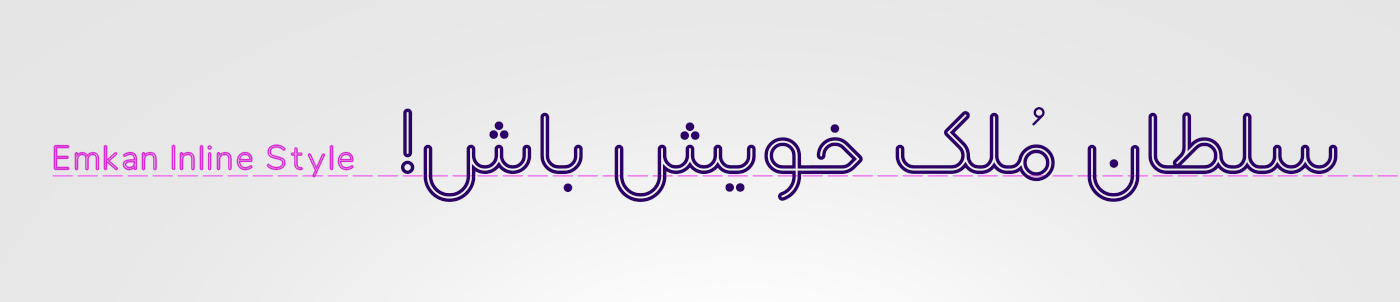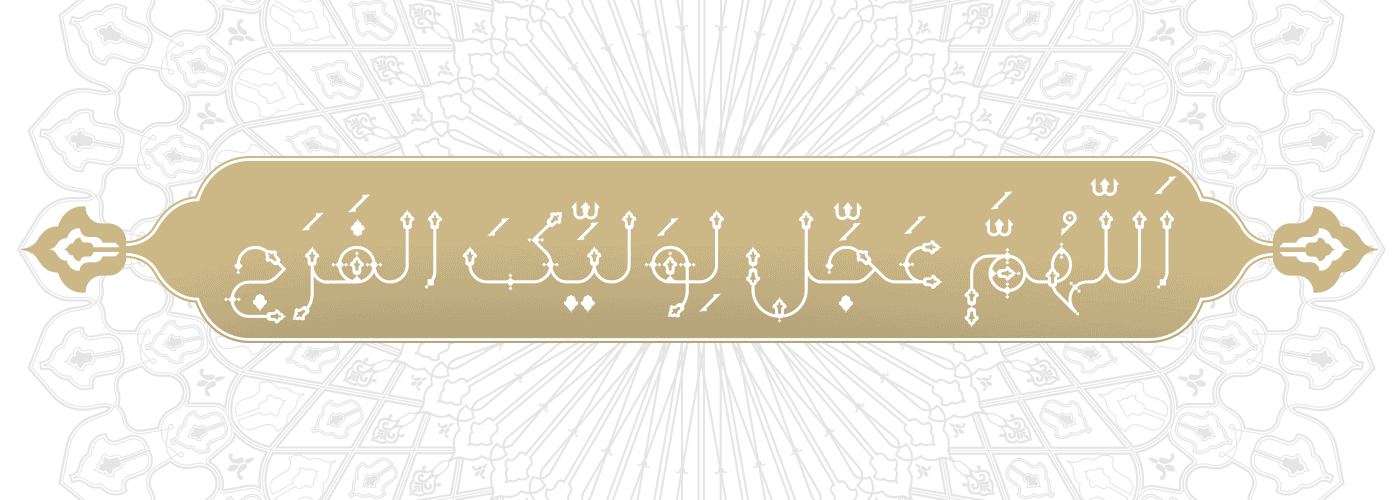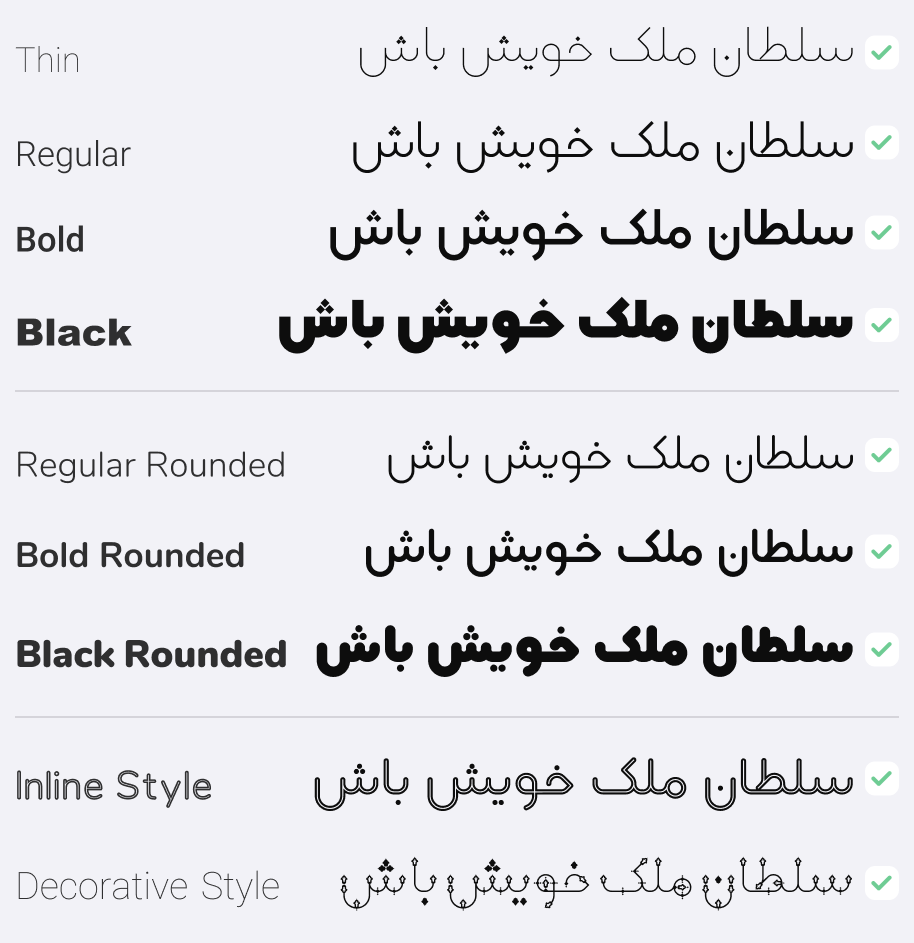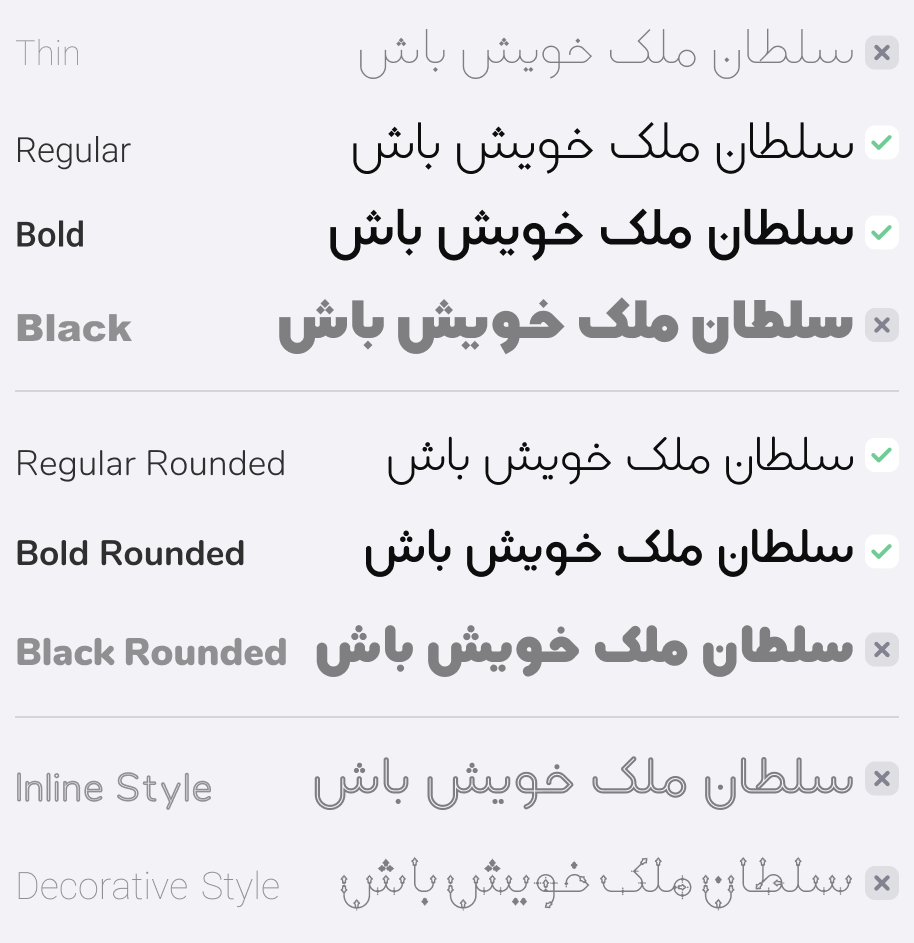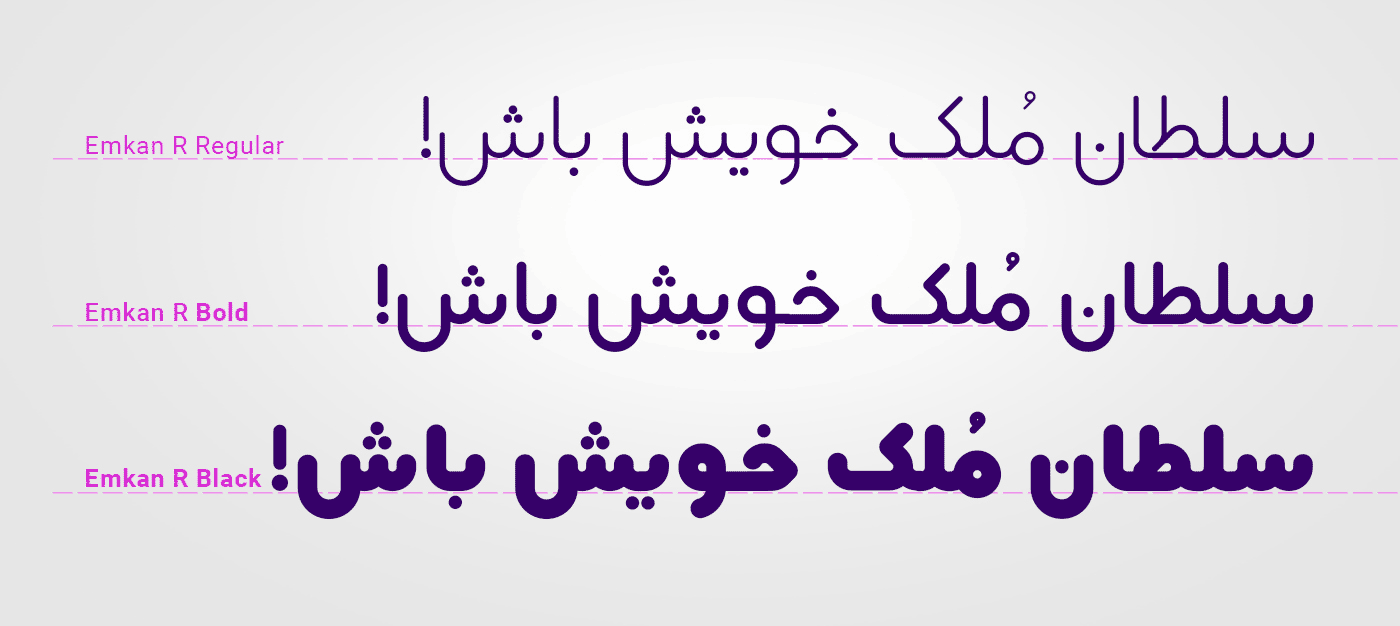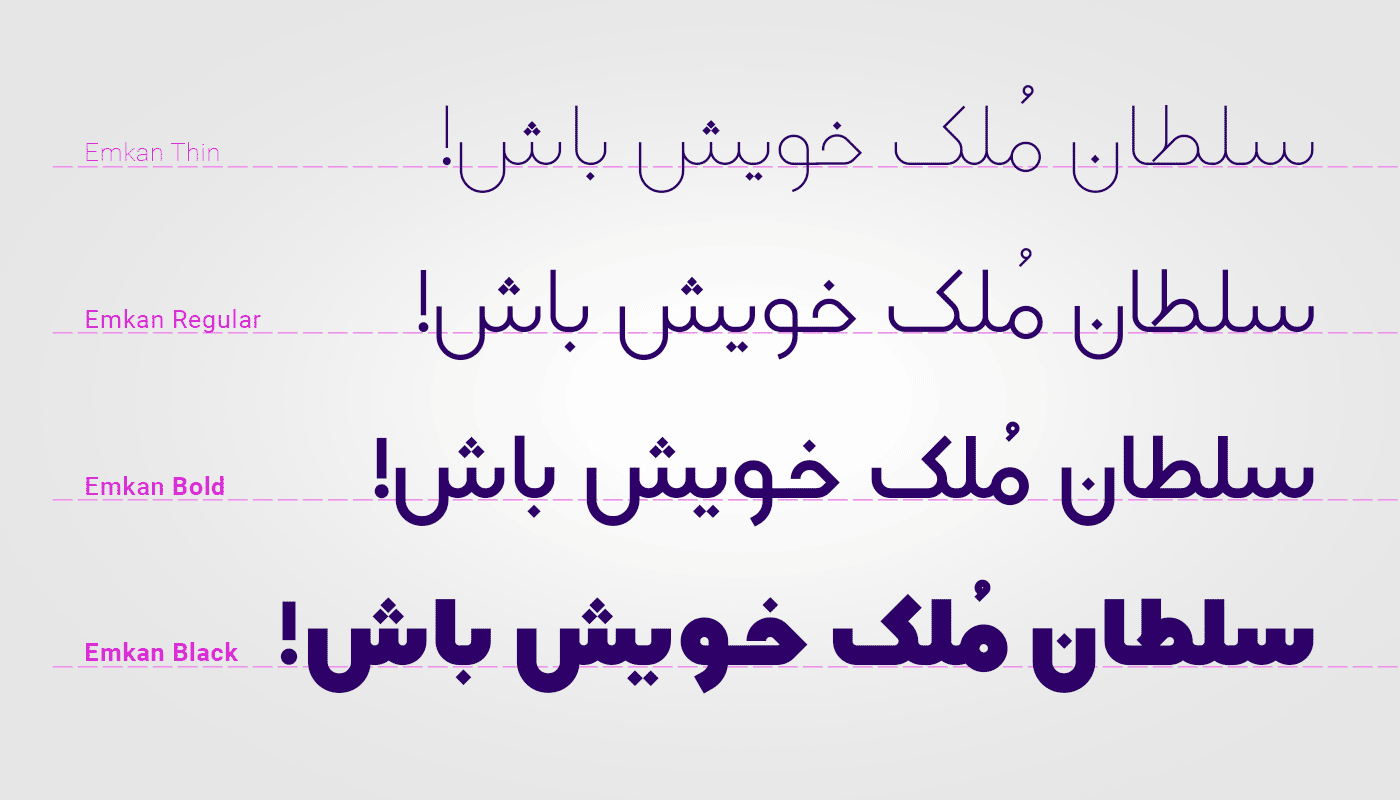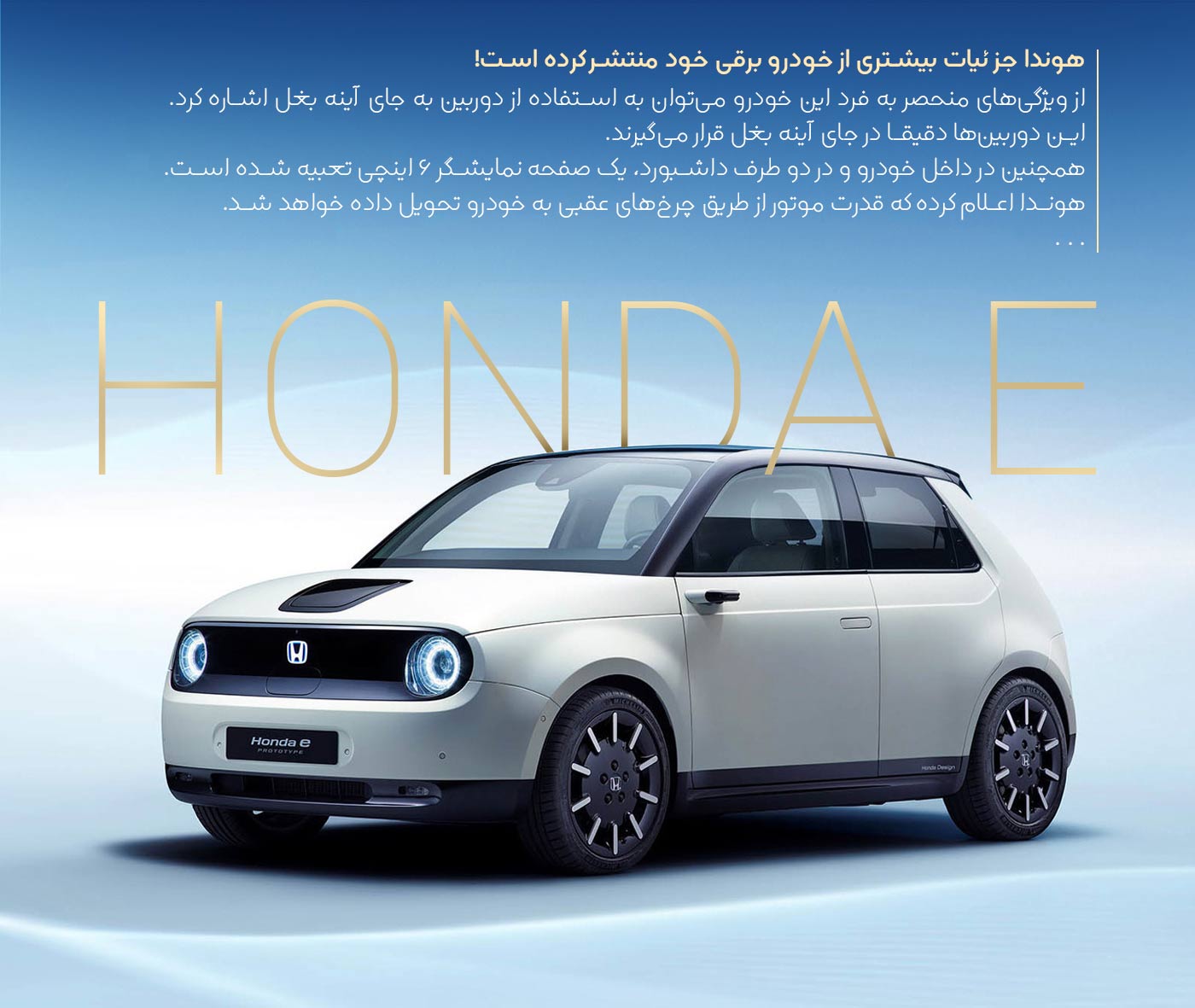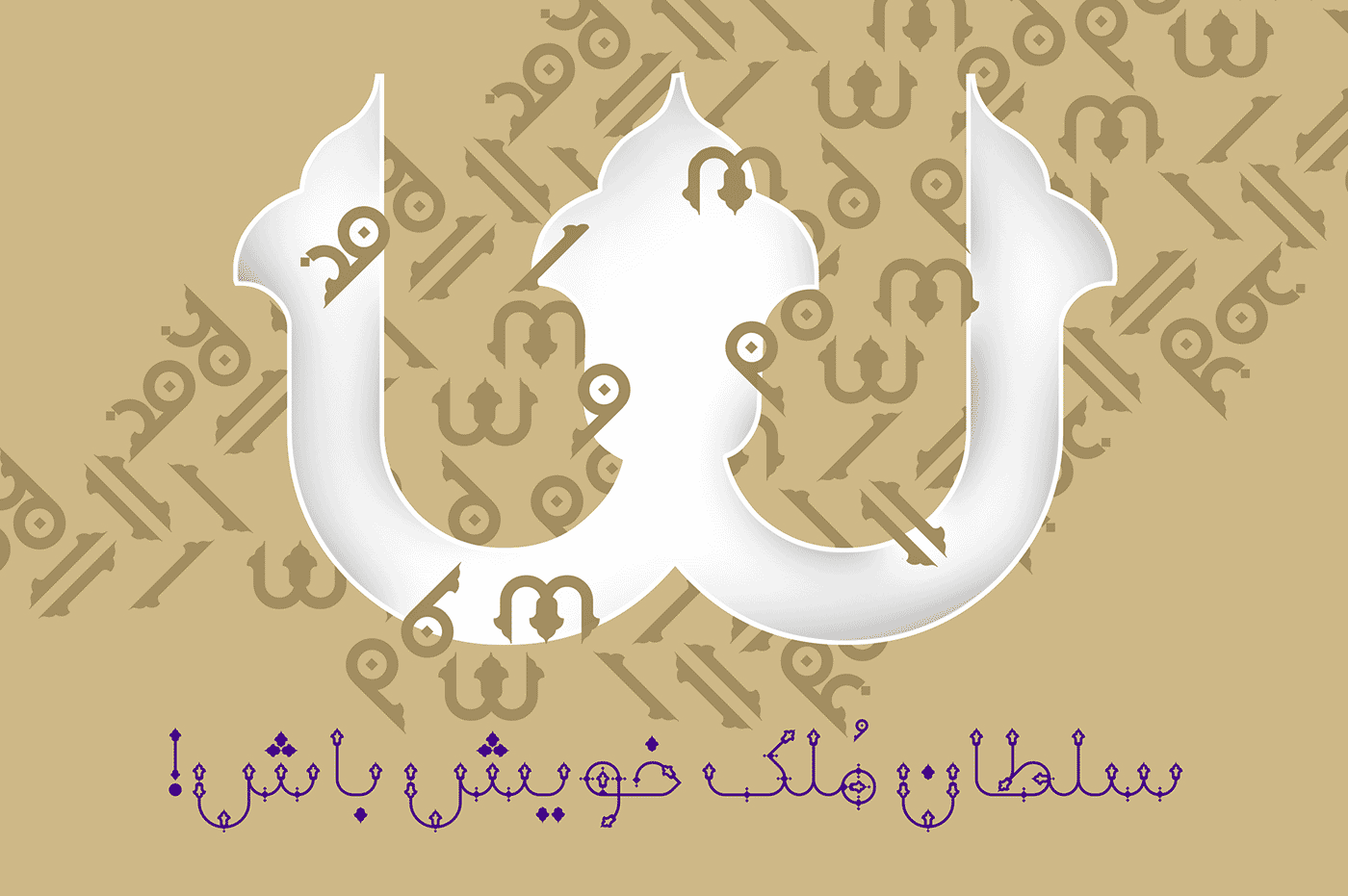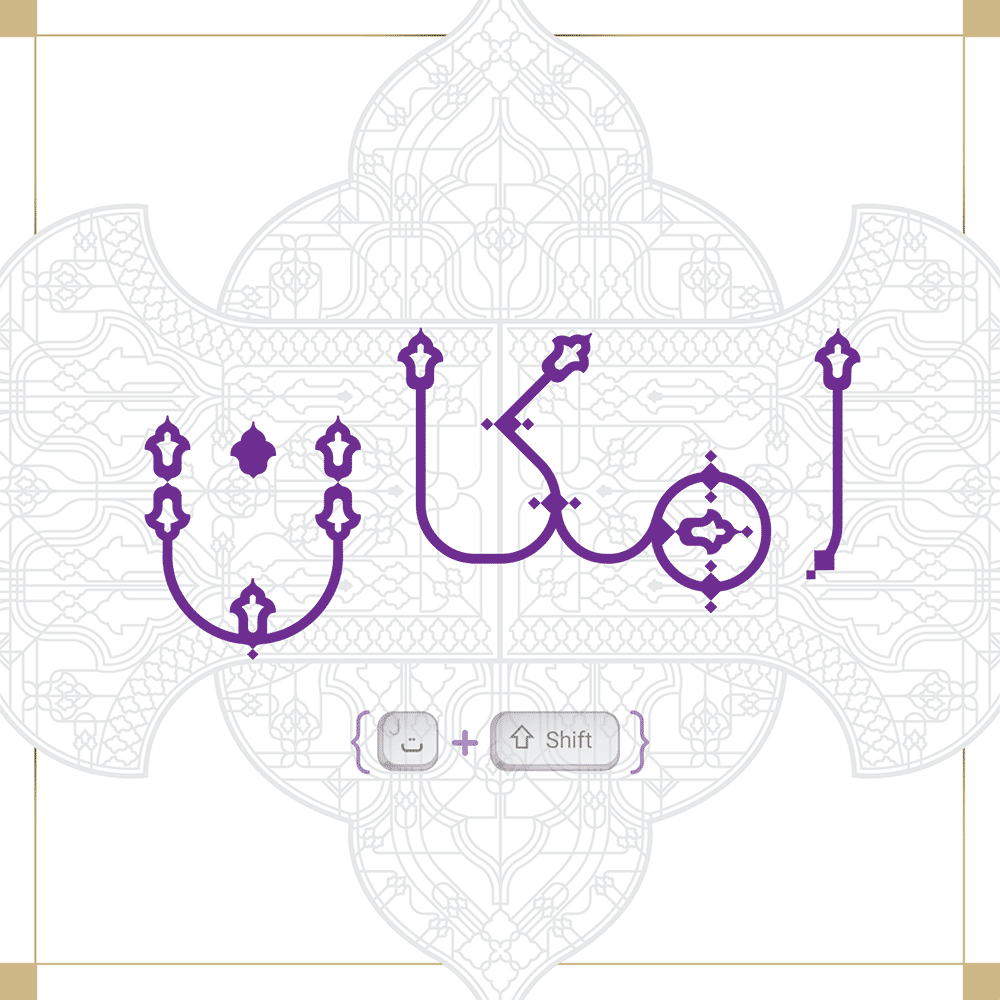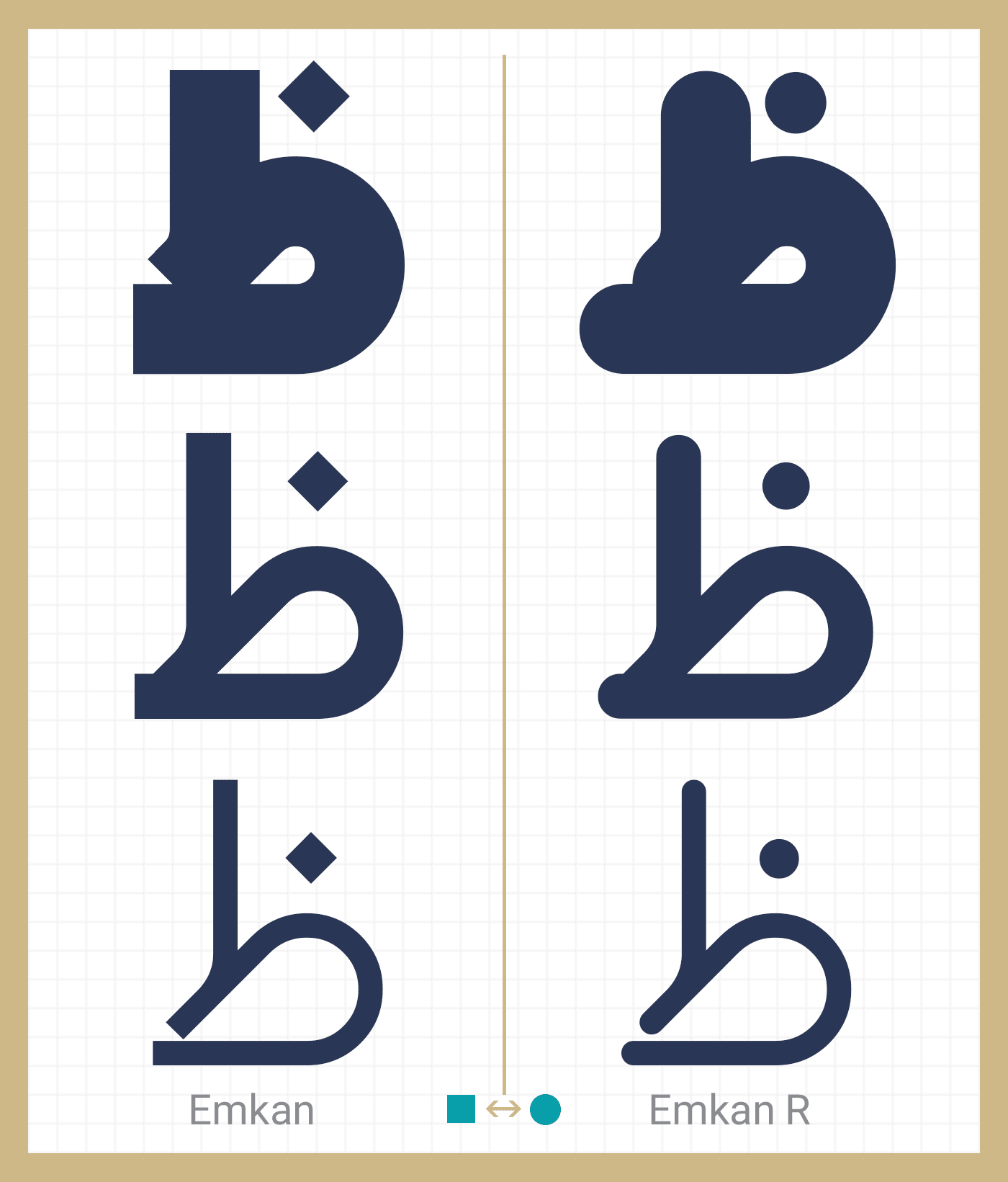
استایل گِرد (Rounded) دارای ۳ وزن معمولی / بولد / سیاه
استایل اینلاین (Inline) دارای ۱ وزن
استایل تزئینی (Decorative) فونت امکان دارای ۱ وزن باریک
فونت امکان دارای تعدادی حروف جایگزین و ترکیبات است که طبق راهنمای موجود در بسته میتوان از آنها استفاده کرد.